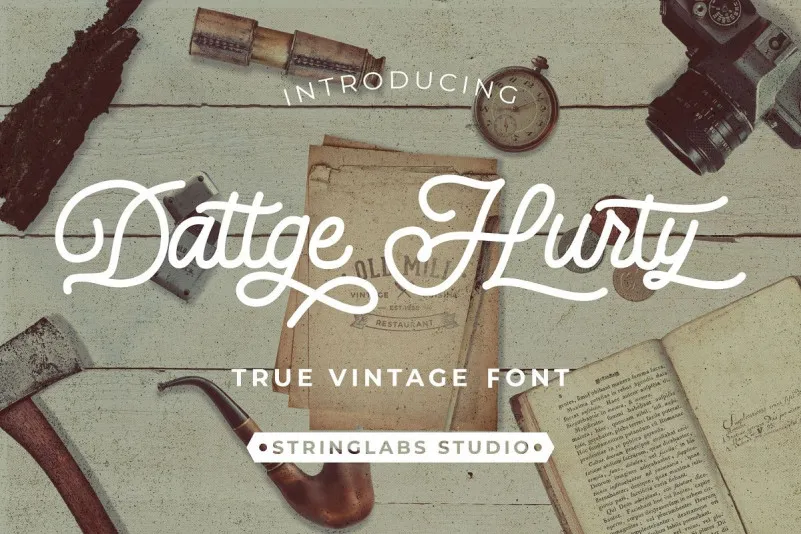
Dattge Hurty – Monoline Retro Font – Download Grátis
Dattge Hurty – Monoline Retro Font é uma fonte script monolínea que transmite alegria e leveza, inspirada no estilo vintage moderno e retro. Esta elegante fonte é perfeita para designers de moda ou empresas que criam produtos fashion como roupas, calçados e acessórios. É também ideal para empresas que precisam de um logotipo diferenciador, cartões de visita, convites de casamento e até mesmo o nome de um barbeiro ou têxtil. Com sua tipografia monocorde e conceito único, esta fonte atende a uma ampla gama de necessidades gráficas, desde um estilo sofisticado até aquele charme alegre que você está procurando para destacar seu projeto. A Dattge Hurty – Monoline Retro Font é uma escolha perfeita se deseja trazer um toque vintage moderno à sua próxima criação.